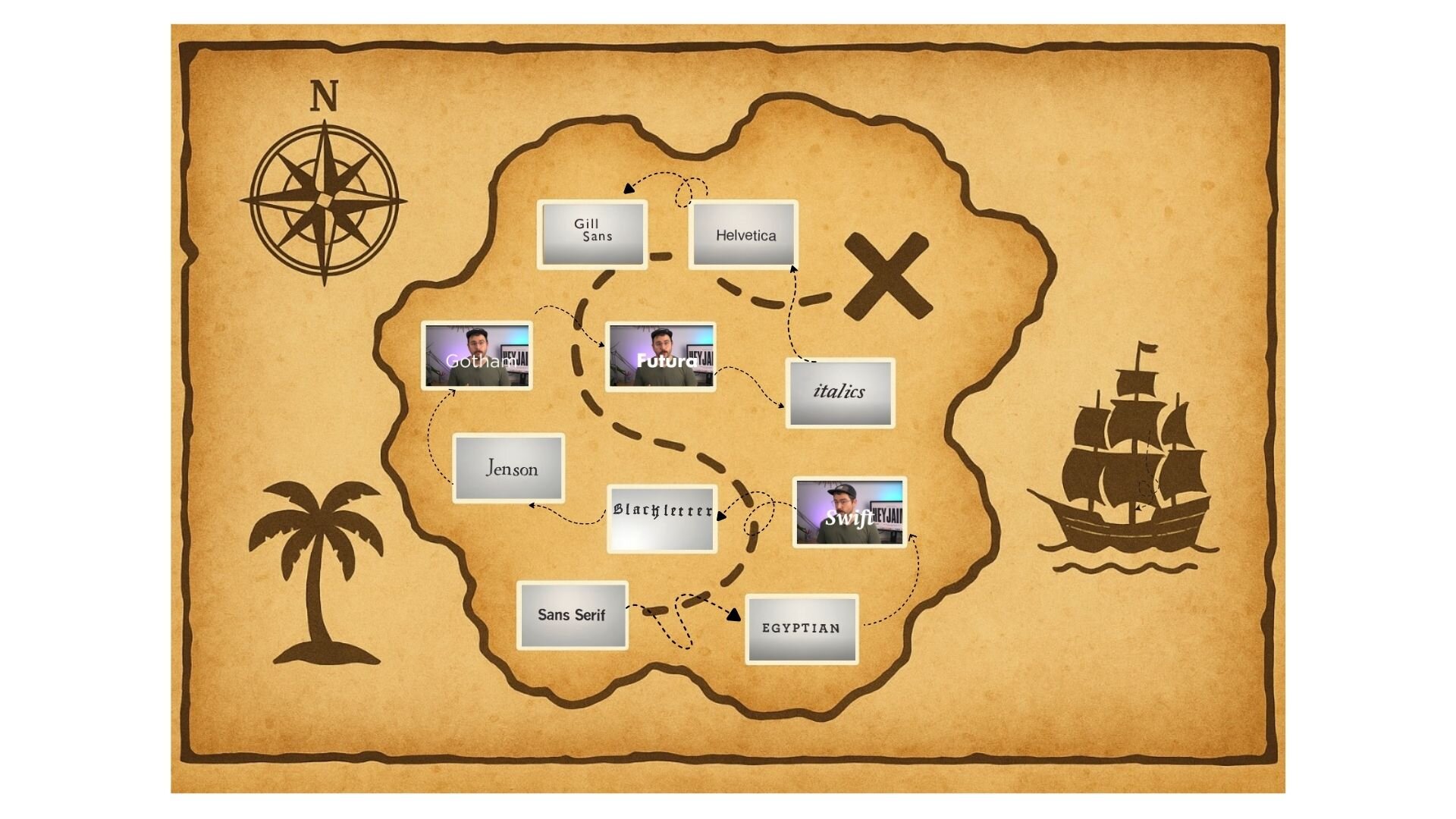
mapa de tesoro de las tipografias
encuentra la respuesta correcta
mapa de tesoro de las tipografias
encuentra la respuesta correcta
1 que significa "sin remates", nombre de tipografia 2 tiene serifas muy gruesas y rectangulares 3 su diseño robusto y legible en imprension 4 tiene trazos goticos, densos y angulosos 5 estlo clasico " humanista del renacimiento 6 se utilizo en la campaña de Obama 7 es una tipografia geometrica 8 ayuda para ahorrar espacio en impresion 9 su caracteristica es su simplicidad y neutralidad 10 pertenece a la categoria de sans serif